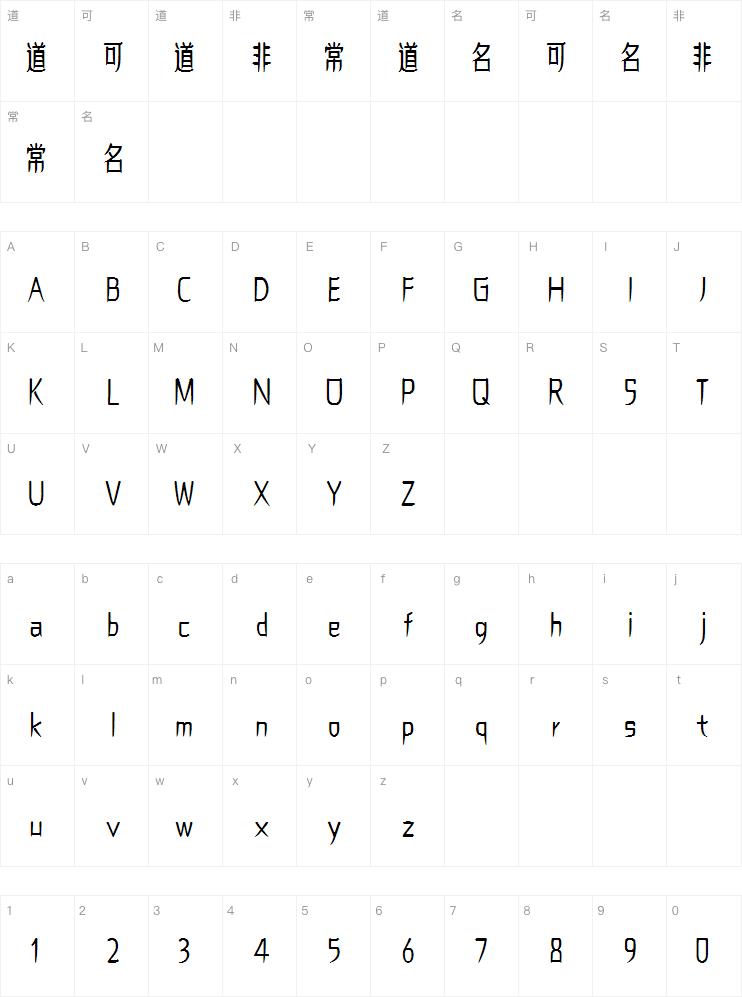
上首古韵体
上首古韵
上首古韵体,笔画平稳厚重、挺拔有力、舒展飘逸、圆润自然、对比适中,受到了中国古代丰富的书法艺术和传统文化的启发,从古籍善本中汲取灵感,提炼出具有代表性的笔画和结构特征,并融入到现代字体设计中,秉持着 “古为今用” 的理念,保留古代书法的美感和韵味,又考虑到现代社会对字体的功能性要求,旨在通过现代设计手法,将古代书法的韵味与现代字体的实用性相结合。适用于搭配标志、广告标语、商业广告等高端属性。
上首古韵体